In ihren fünf Jahren als international tätige Lettering-Künstlerin hat es die aus Buenos Aires stammende und heute in Berlin lebende Martina Flor bereits zu einem beachtlichen Ruf gebracht. Neben der Fertigung ihren Auftragsarbeiten vermittelt sie ihre Kenntnisse auch in Workshops und nun einem eigenen Buch, das im Verlag Hermann Schmidt Mainz erschienen ist.
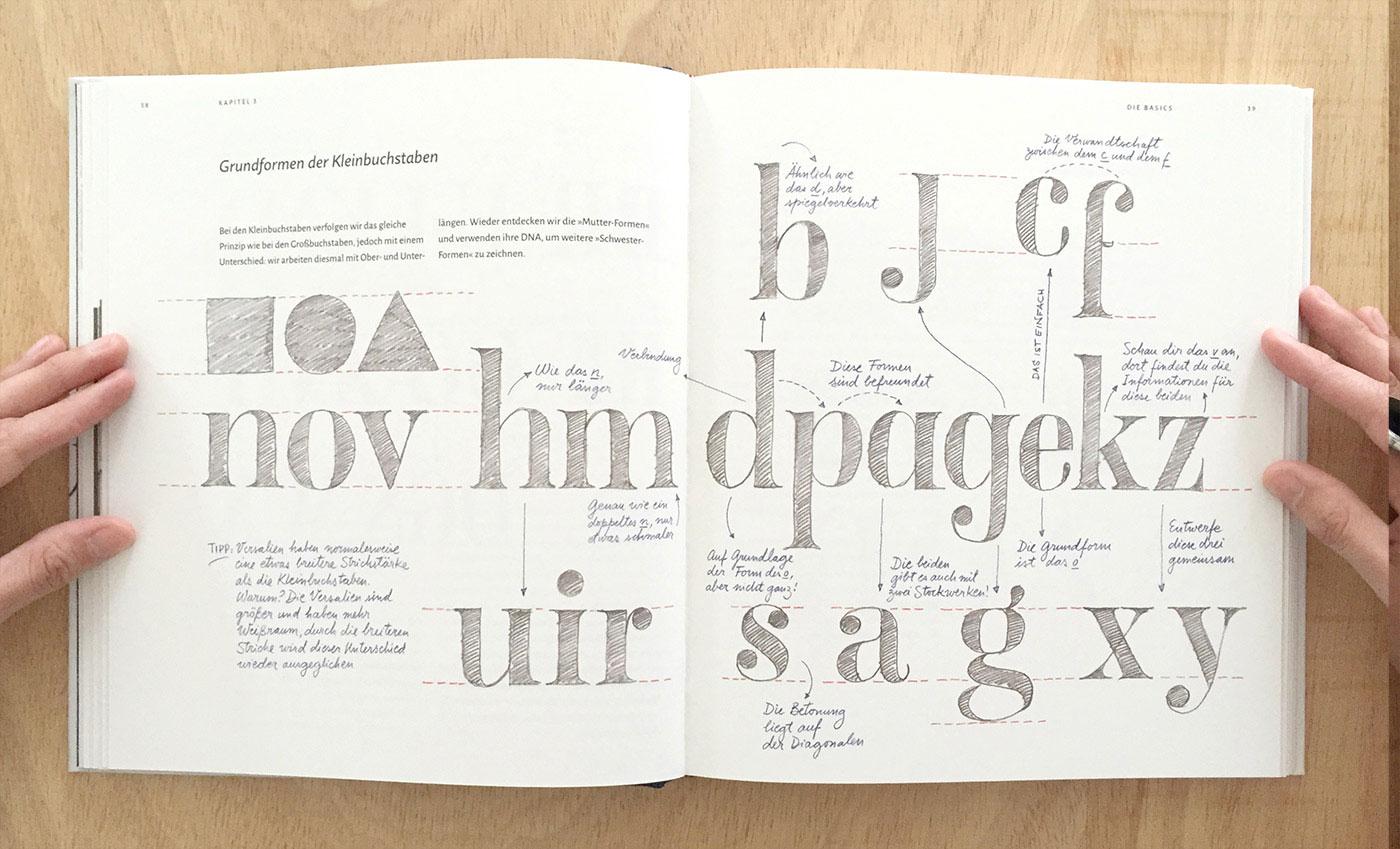
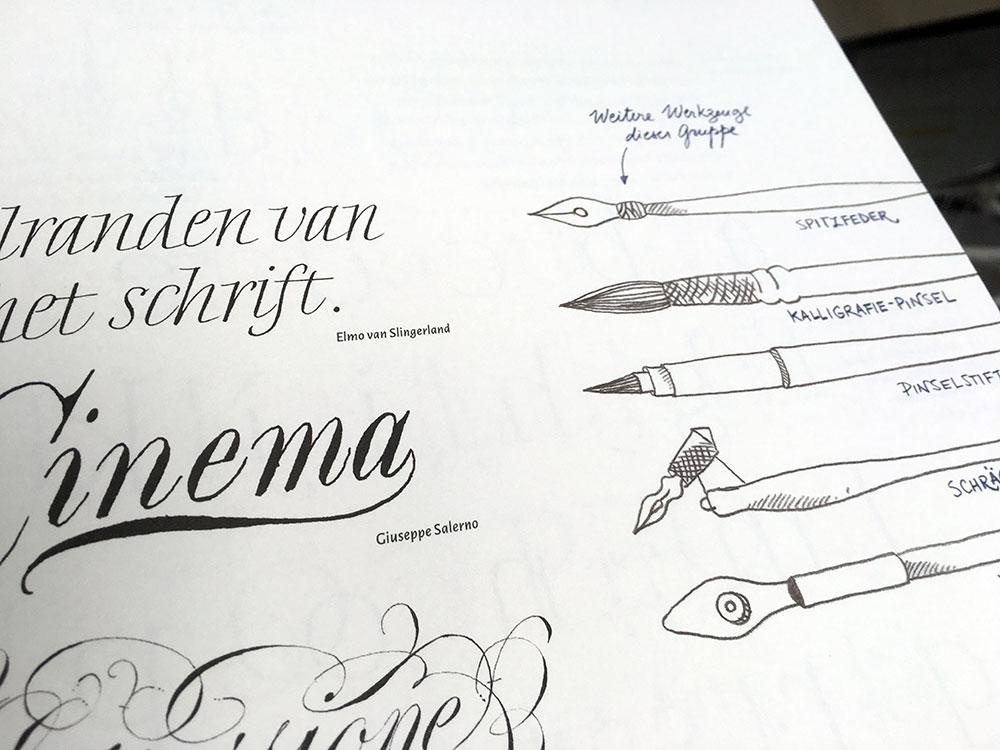
In »Lust auf Lettering« gibt Martina Flor Einblick in ihre Arbeitsweise und vermittelt Fachwissen rund um Schrift, Kalligrafie und Lettering. Das Buch gliedert sich folgendermaßen:
- Visuelles Storytelling – Lettering in Abgrenzung zu Kalligrafie und Typedesign
- Das typografische Auge – Von der Bedeutung des Beobachtens
- Basics – Von der DNA der Buchstaben
- Werkzeuge in ihre Anwendung – Von Feder, Pinsel und anderen Tools
- Spielwiese für Lettering Designer – Von der unendlichen Vielzahl gestalterischer Stile
- Komposition und Dekoration – Von Struktur, Hierarchie und Verzierung
- Schriften skizzieren – Von der ersten Skizze zum komplexen Entwurf
- Analog zu digital – Von Ankern und Vektoren
- Der letzte Schliff – Von Farben und Texturen
- Work in Progress – Auf dem Weg zum Lettering-Profi
Wie man sieht, gibt das Buch einen Gesamtüberblick über die Arbeit eines Lettering-Designers: Von Werkzeugen, Schriftstilen und Arbeitsweisen während des Entwurfs bis hin zur Reinzeichnung/Vektorisierung und der Arbeit mit Kunden wird alles besprochen. Die vielen Illustrationen machen das Buch dabei kurzweilig und weisen auf leicht verständliche Weise auf die wichtigsten »Dos and Don’ts« hin.
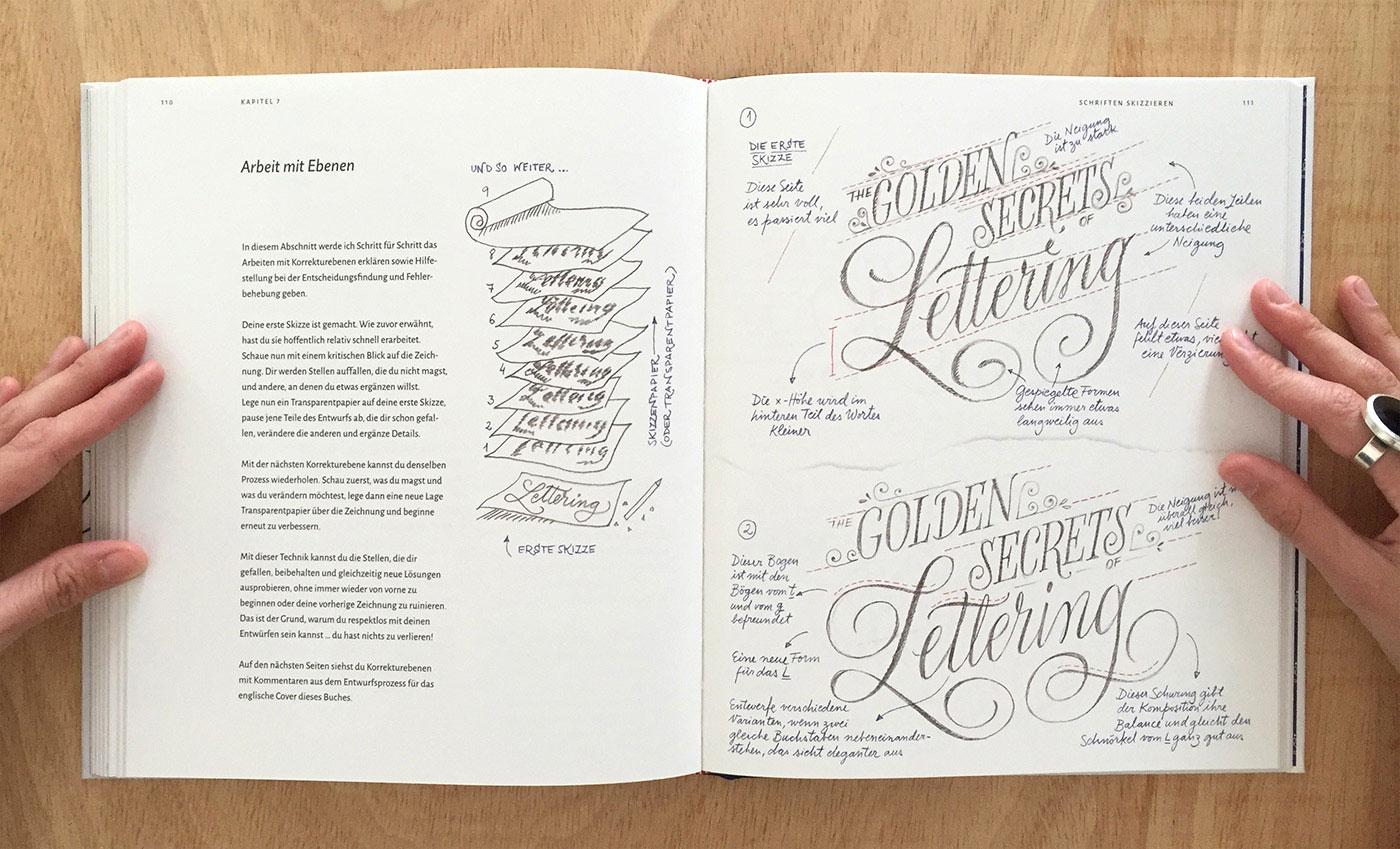
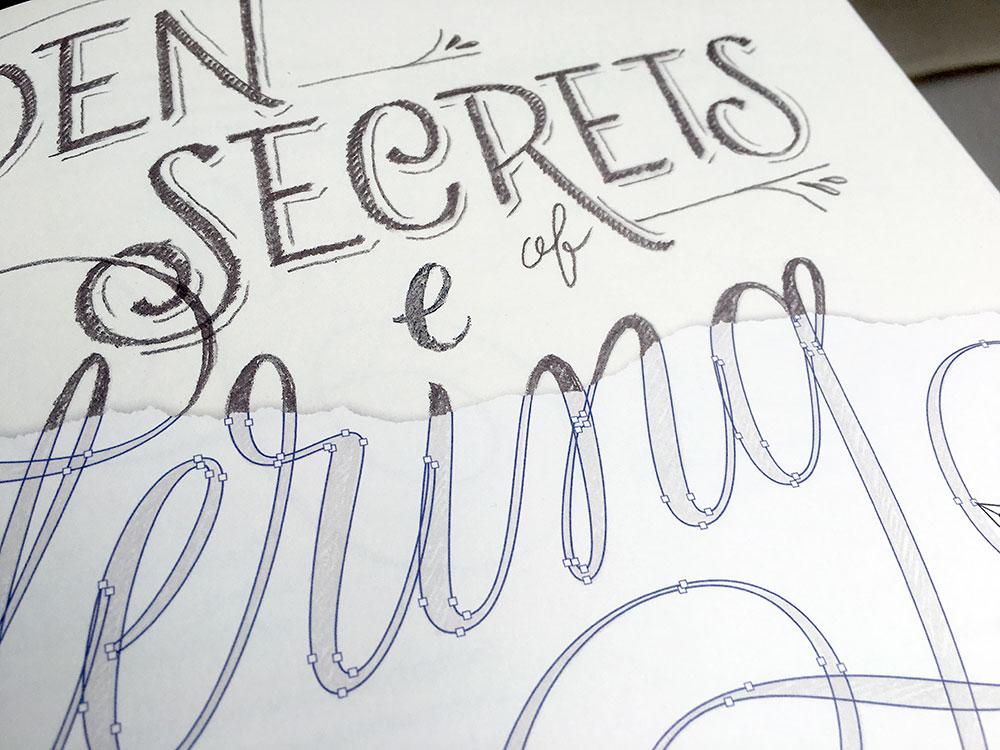
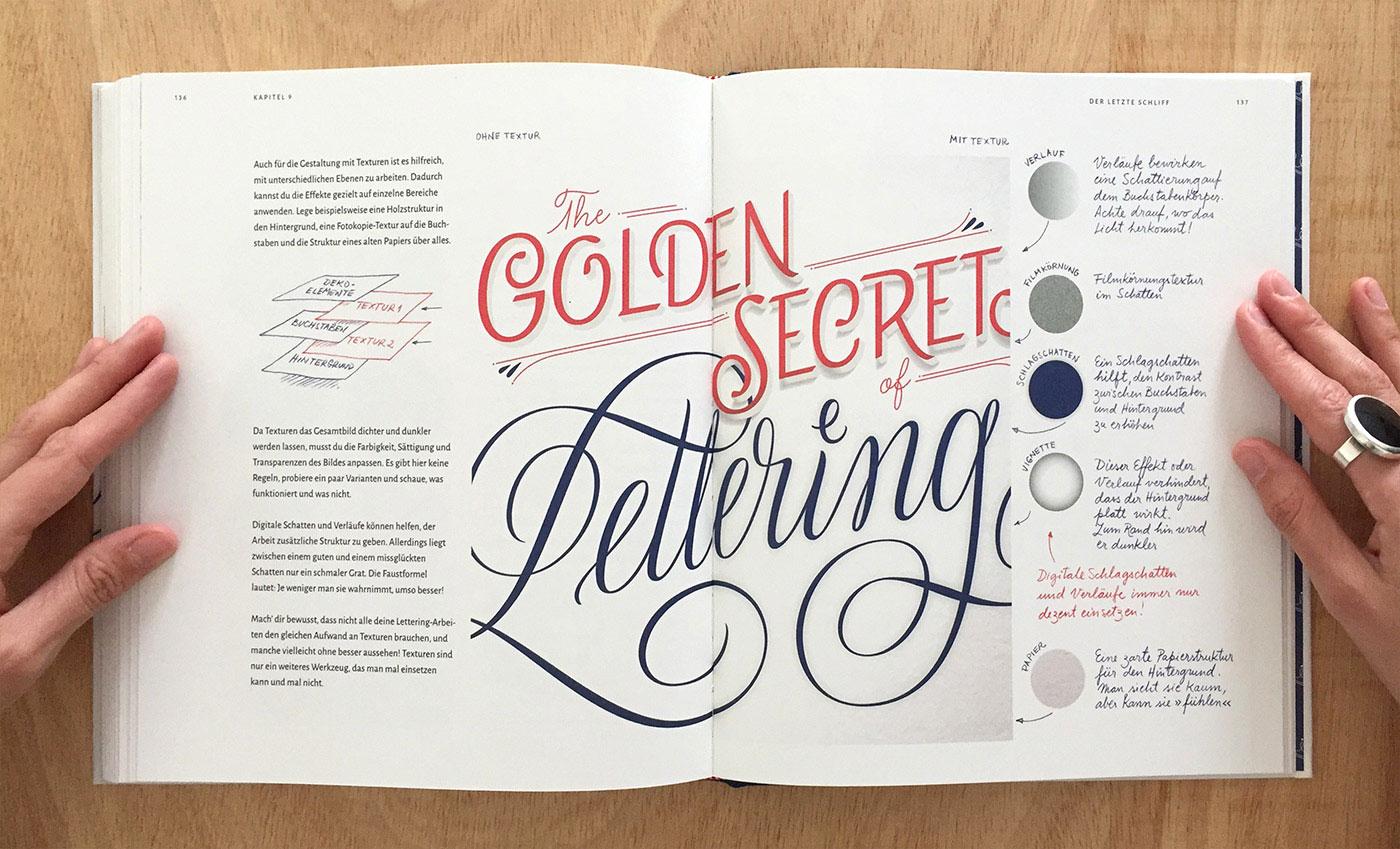
Es liegt aber in der Natur der Sache, dass ein Buch über kunsthandwerkliche Techniken Kurse und die notwendige Übungspraxis nicht ersetzen können. So ist Lust auf Lettering also weniger ein Lehrbuch, als vielmehr ein kurzweiliger Überblick über die Arbeit eines Lettering-Künstlers.
Das Buch zeigt sich in der üblicher, hochwertigen Schmidt-Qualität. Die 168 Seiten als Hardcover sind detailverliebt gestaltet und passend zum Thema über weite Strecken in Lettering-Stil gestaltet, das heißt, Texte sind oft nicht gesetzt, sondern geschrieben und die Seiten wie abfotografierte Blätter auf einem Schreibtisch dargestellt.
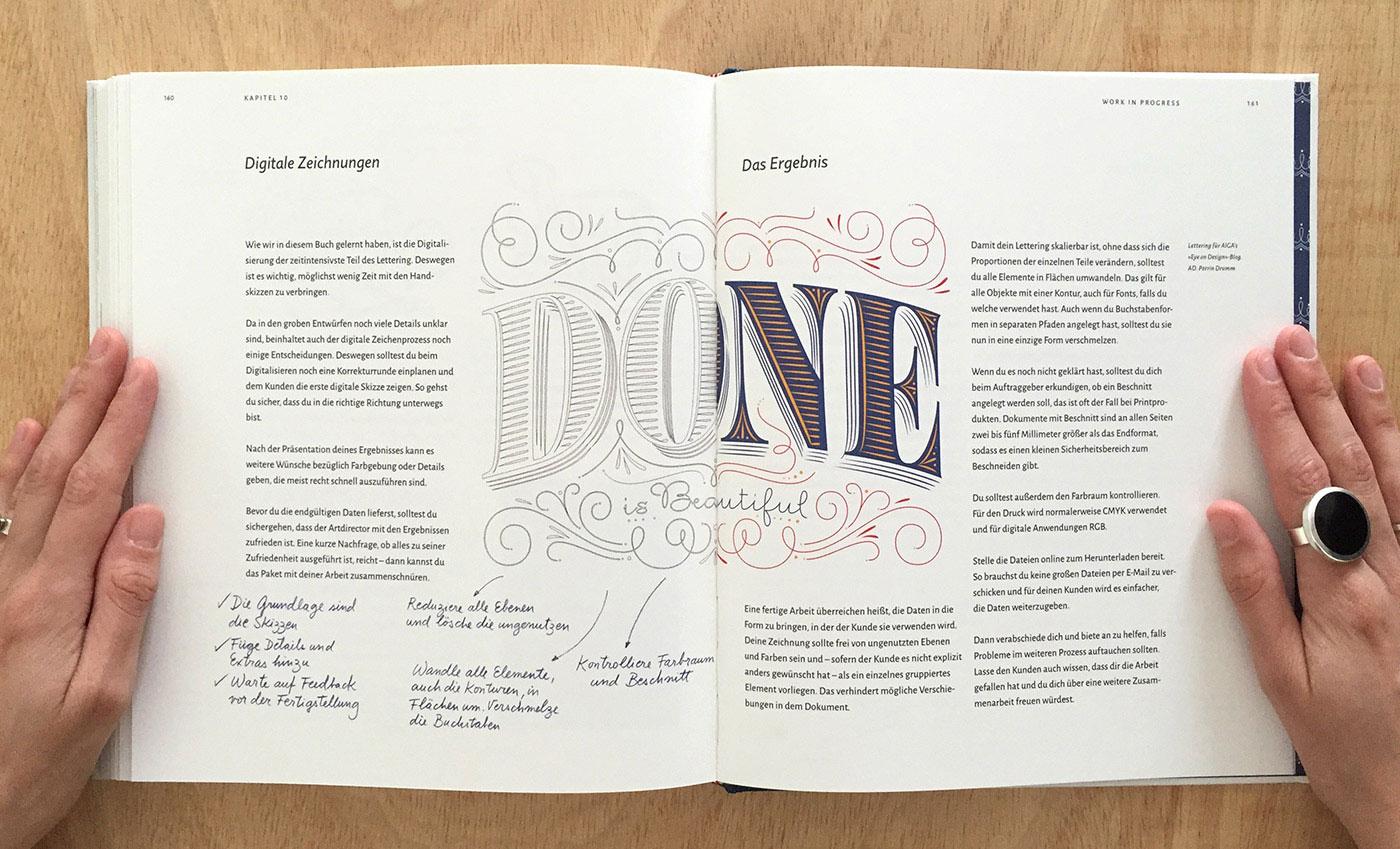
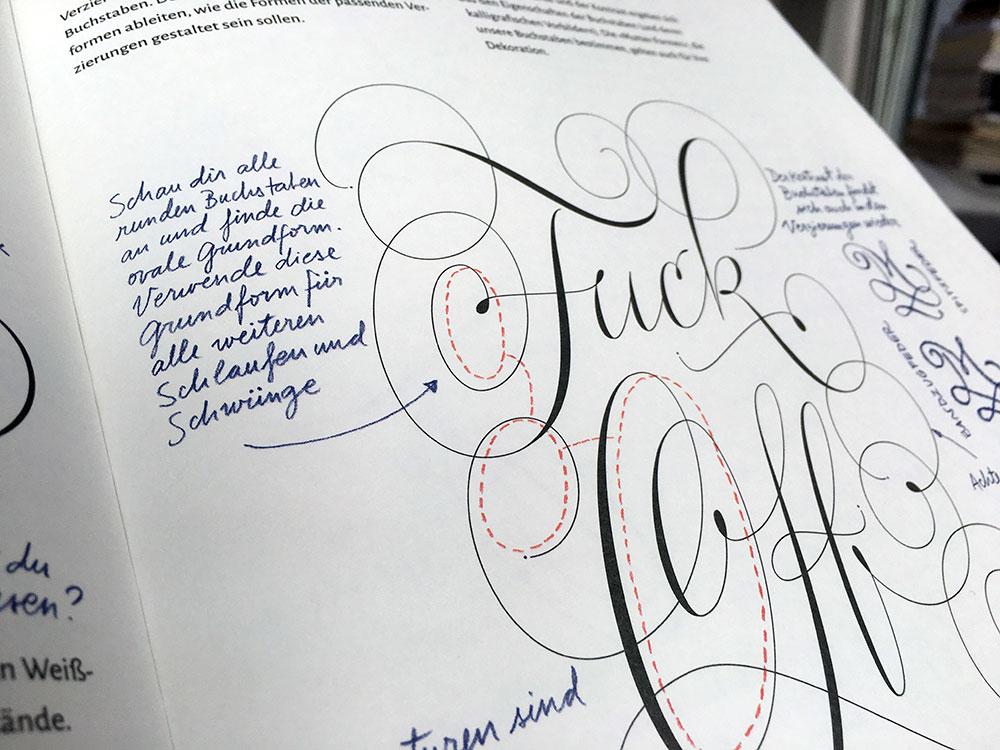
- Schriften: Alegreya Sans, Alegreya Serif, Quire Sans